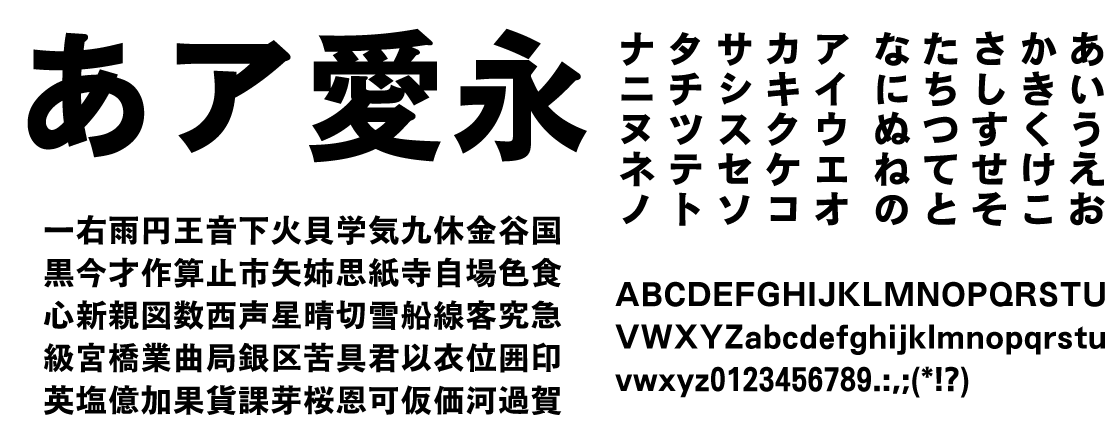
モトヤゴシック
ゴシック体は、明朝体のように横線や縦棒を装飾するウロコや、セリフといったものが無いので、骨格線そのものが命である書体です。また横線にも画数に応じた太さの調整が必要となるので、太さの統一性を持たせるのが非常に難しい書体とも言えます。モトヤのゴシック体ファミリーは、この二つの命題を克服すると同時に、背勢表現(縦棒や横線の両端につけるラッパ状のアクセント)を施すことにより、伝統と力強さと柔らかさを同時に感じさせる書体となっています。